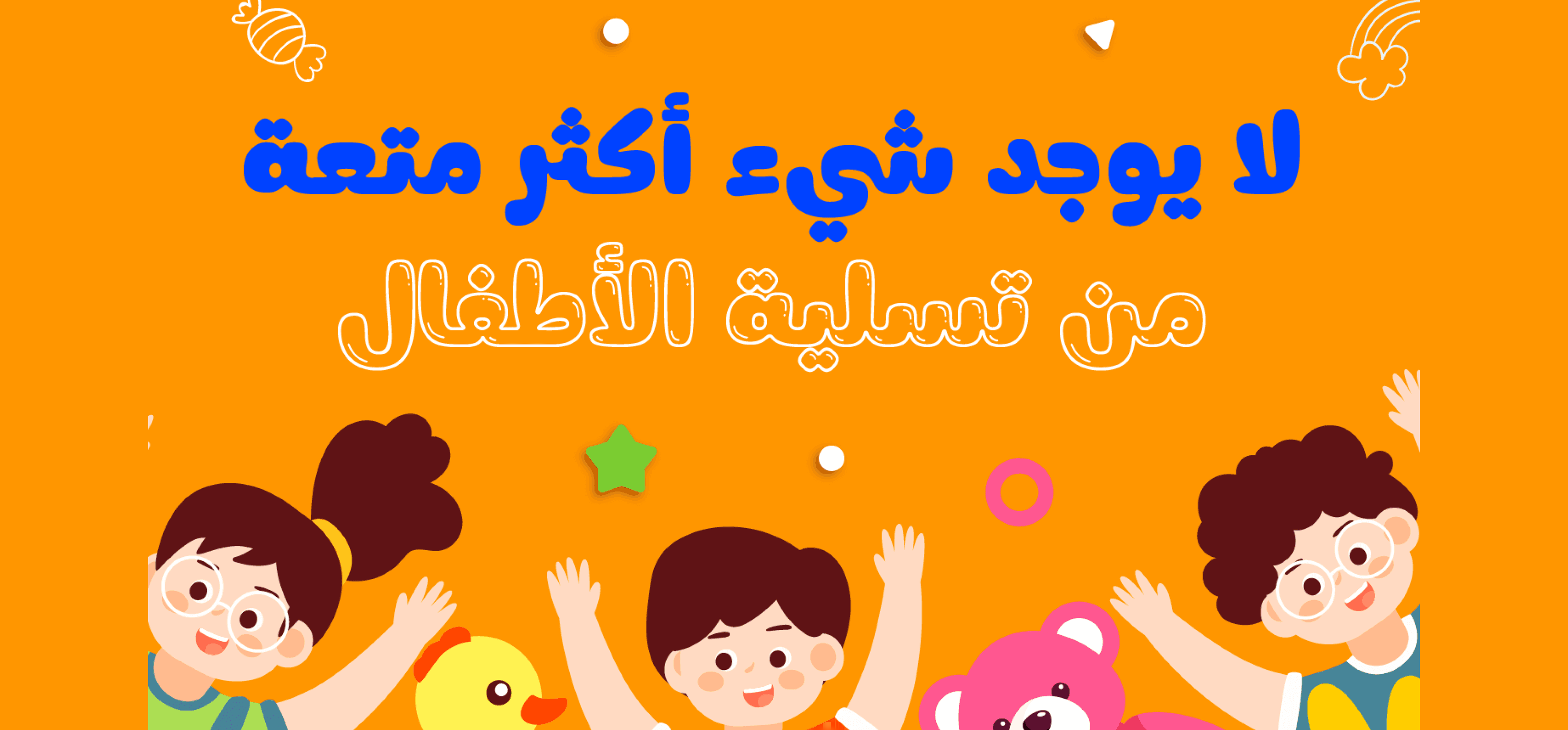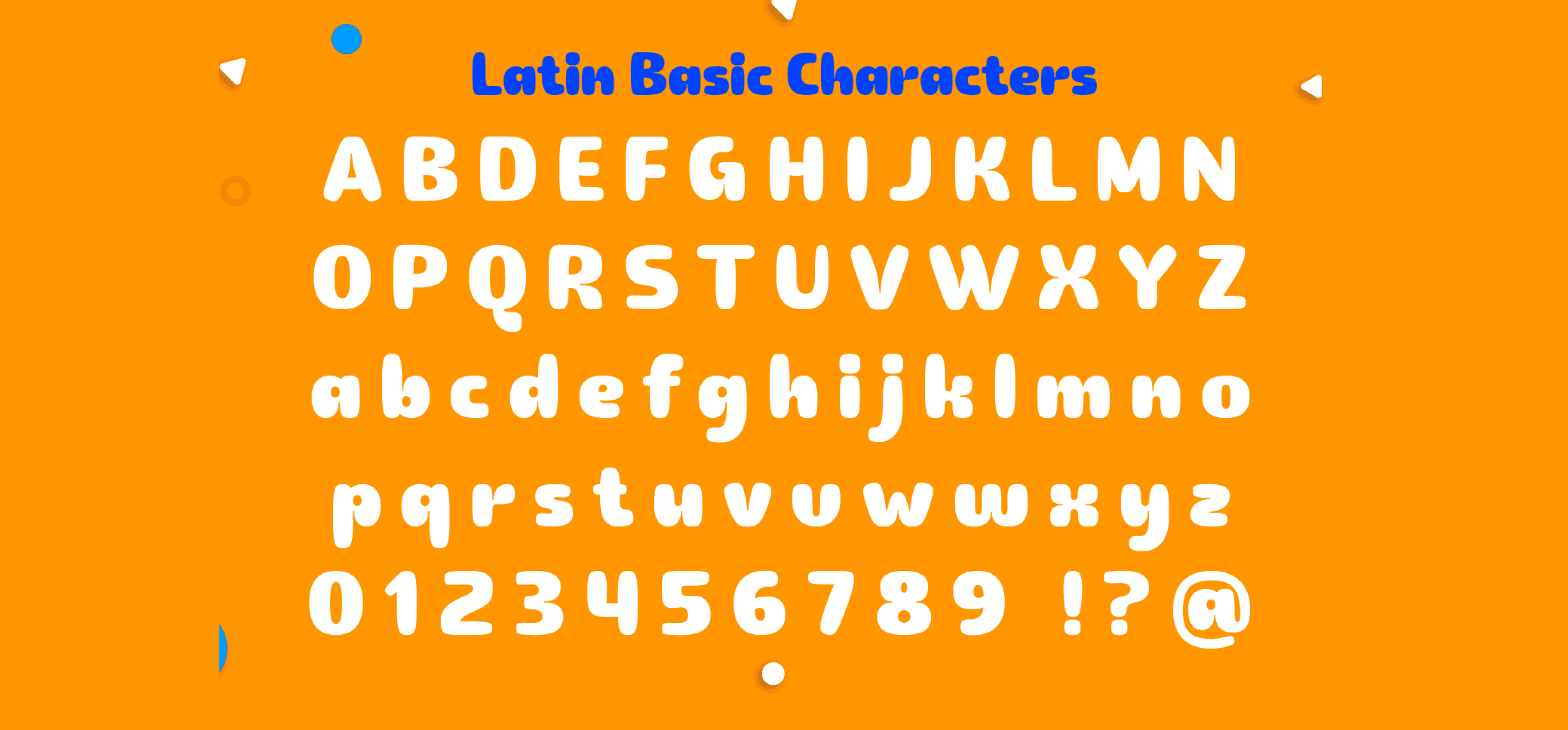
خط Lutfey Arabic هو خط ساحر وودود يتميز بأشكاله الجريئة واللطيفة في الوقت نفسه. يضفي مظهره السميك إحساسًا بالمرح والثبات. يتميز الخط بخطوطه الناعمة المصممة بعناية، خاصة على الحواف الخارجية، مما يخلق مظهرًا بصريًا جذابًا. كما تضيف تفاصيل "حبس الحبر" الدقيقة في كل زاوية لمسة من الأناقة والرقي.